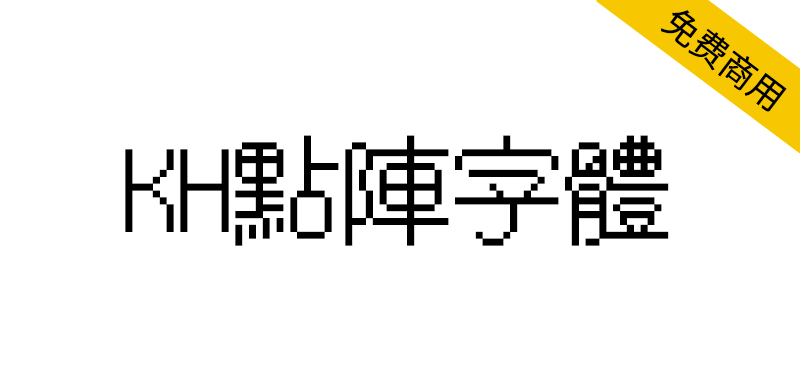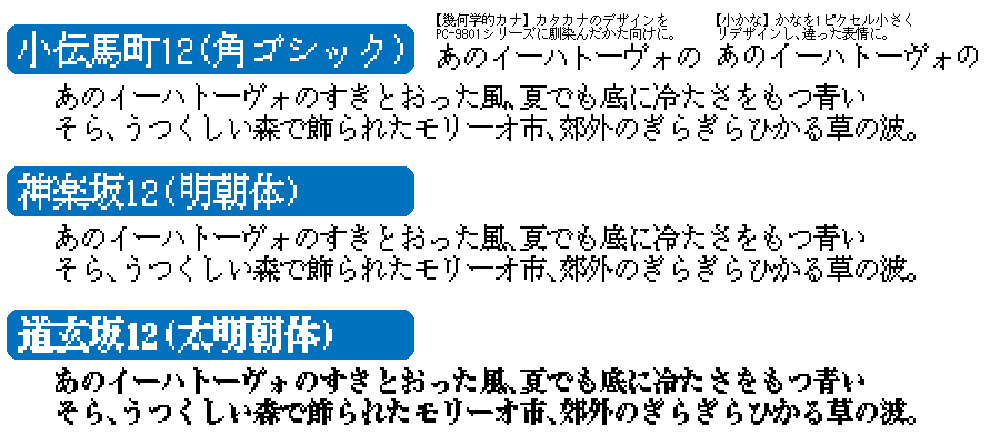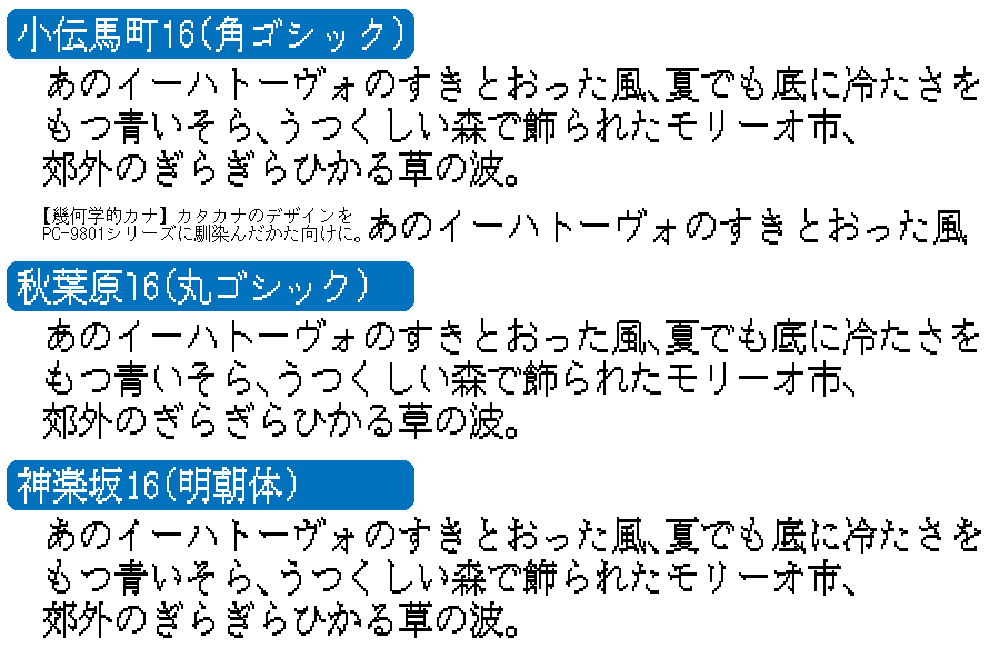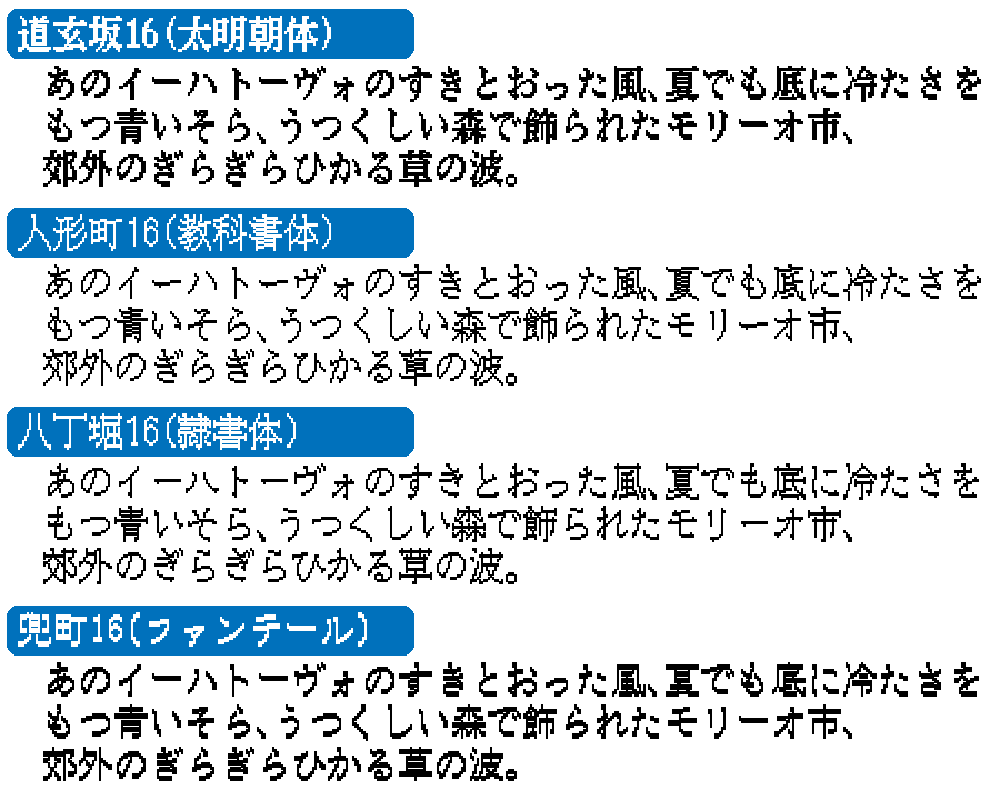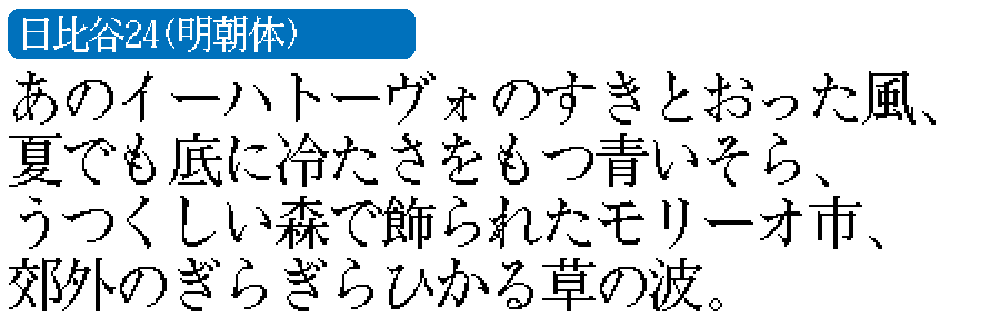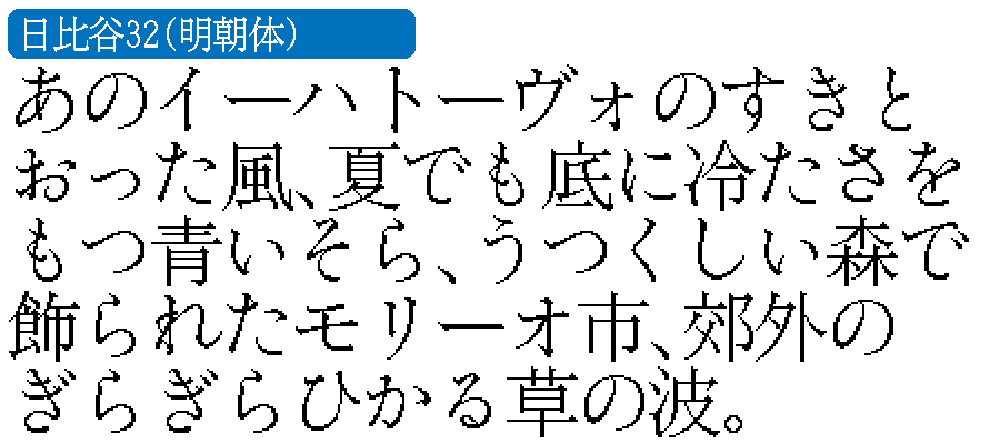
KH点阵字体(KHドットフォント)是一种由粗糙像素点构成的位图风格字体系列,包含有15款富有表现力的字体。所有字体均采用TrueType格式的等宽轮廓字体,可在Windows、Mac、Linux等多种系统环境中使用。
这款字体系列由字体设计师平木敬太郎先生于1991至1996年间设计完成,其最初是为X68000系列(夏普1987年推出的电脑系列)等平台开发的高品质点阵字体。现由自制字体工坊将其重新构建为TrueType格式。
本系列包含12-32像素方块的15款独特高品质字体,其设计初衷虽为系统字体,但在高分辨率设备和轮廓字体主流的当下,其点阵特性反而使其特别适合创意设计、视频制作等领域。例如可完美呈现8-16位元风格(俗称"红白机风""超任风")、或早期功能手机邮件界面的复古数字美学——这与同属免费点阵字体的PixelMplus应用场景类似。
所有字体均包含JIS第二水准汉字库。除部分字体(小传马町12系/道玄坂16/神乐坂16/日比谷32)外均支持竖排显示。内嵌位图数据使得在Windows系统等倍显示时能呈现清晰像素效果(类似MS Gothic小字号时的锐利点阵显示)。
KH点阵字体系列(KHドットフォントシリーズ)的15种不同风格的点阵像素字体:小伝馬町12 / 幾何学的カナ / 小かな (角ゴシック)、神楽坂12 (明朝体)、道玄坂12 (太明朝体)、小伝馬町16 / 幾何学的カナ (角ゴシック)、秋葉原16 (丸ゴシック)、神楽坂16 (明朝体)、道玄坂16 (太明朝体)、人形町16 (教科書体)、八丁堀16 (隷書体)、兜町16 (ファンテール)、日比谷24 (明朝体)、日比谷32 (明朝体)
KHドットフォントは、荒いドットで構成されたビットマップ風のフォントシリーズで、表情豊かな 15 書体で構成されています。これらはすべて TrueType 形式の等幅アウトラインフォントですので、Windows や Mac、Linux などの各種環境で使用することができます。
本フォントシリーズは、書体デザイナーの平木敬太郎氏により1991年から1996年にかけてデザインされ、現在は X68000 シリーズ (1987年に発売されたシャープのパソコンシリーズ) 向けなどの形式として頒布されている高品質なドットフォントを、自家製フォント工房が TrueType フォーマットとして再構成したものです。
本フォントシリーズには、12~32ピクセル四方で構成された、他にはない個性的で高品質な 15 の書体が含まれます。本来はシステムフォントとして設計されたフォントですが、デバイスのディスプレイ解像度が上がり、アウトラインフォントが主流となった現在では、ドットフォントという特徴を活かし、デザインや動画制作などのクリエイティブな方面にもご活用いただけるかと思います。
たとえば、同じフリーのドットフォントとして人気の高い PixelMplus の頒布ページで例示されているような、8~16ビット的な表現、つまり一般に「ファミコン風」「スーファミ風」などと呼ばれる表現や、ガラケー初期のメール的な表現など、少しレトロチックなデジタルのイメージをあらわすのにも適しています。
各フォントは、JIS第2水準までのすべての漢字を含みます。一部 (小伝馬町12系統・道玄坂16・神楽坂16・日比谷32) を除き、縦書きにも対応しています。また、ビットマップも埋め込まれていますので、たとえば Windows でピクセル等倍で表示させると、ビットマップで表示されます (つまり、MSゴシックの小さいサイズのように、くっきりしたドットで表示されます)。